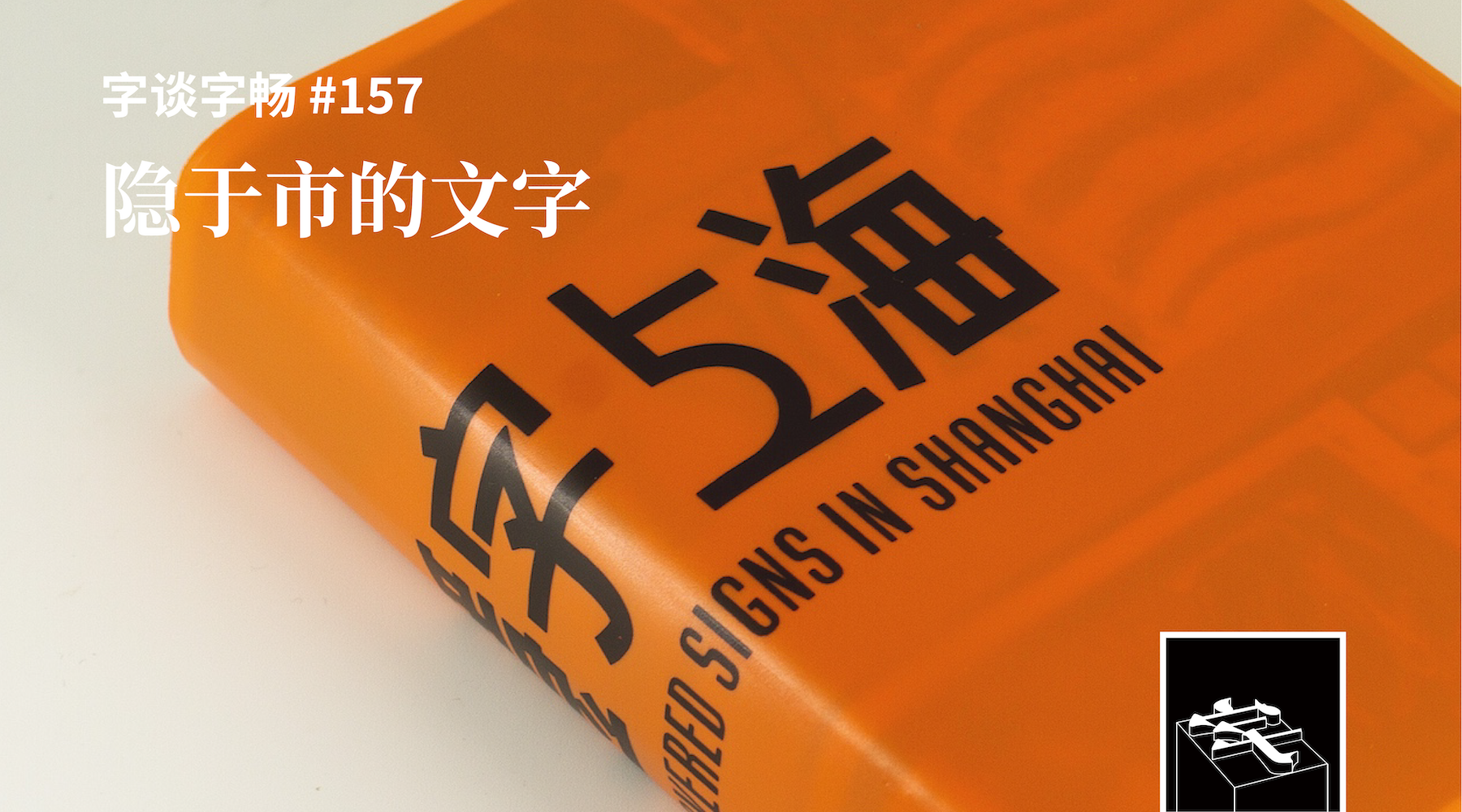
一部隐于书市的影像字典,收录一座城市被隐蔽的变迁史。今天的一小时,我们邀请编辑 Mira,为我们讲述《隐字上海》的出版故事——关于作为摄影师的作者,关于成为照片的文字,关于编辑策划,关于设计。
- 格里董、施佳宇、沈健文摄影,应宁、王诗韵编辑.《隐字上海》(Uncovered Signs in Shanghai).The Type,2020.
- 《他们收集「没人要的字」,我们为此做了一本「字典」》,Mira 所撰的《隐字上海》介绍文章及作者访谈,刊于 The Type
- 格里董,城市漫游者、上海记忆收集人
- 《你的地方·回顾|上海弄堂最后的人间烟火气》,施佳宇发表于《澎湃新闻》的摄影作品
- 「城市漫步」,《澎湃新闻》专栏,沈健文担任编辑
- 《隐字上海》书中照片的拍摄地点
- 《隐字上海》装帧设计由大气设计事务所的陈妍和杨恒斌完成,封面美术字由应永会设计
- 《隐字上海》入选第五届中国摄影图书榜「年度自制摄影图书」